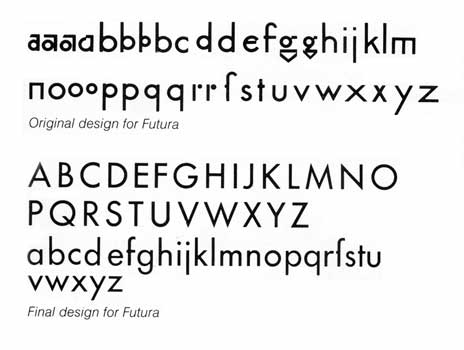
[Suche Bild] Original Designs der Futura von Paul Renner
ich bräuchte für eine Studienarbeit ein Bild von Renners Original Entwürfen der Futura (siehe oben) in guter (na ja, sagen wir mal in besserer) Auflösung. Google bringt mir keine brauchbaren Bilder. Weiß jemand wo ich da fündig werden könnte?
in Christopher Burkes «Paul Renner - The art of typography» finden sich eine große Doppelseite und halbseitige Abbildungen von Renners Reinzeichnungen.
Solche Scans dürften auf die Schnelle die beste Methode sein, ordentliches Bildmaterial aufzutreiben!
Aber vielleicht gibt es ja schon Scans im Netz?
Die Futura von E+F oder URW++ (ich glaube, es war E+F) enthält aber bestimmt nur die bekannten Sonderzeichen agmn&, die es auch in der Bleisatz-Type gab.
Burke stellt aber auch zB. 11 unterschiedliche g Varianten vor (Seite 92), die aus der Entwurfszeit (1925) der Futura stammen.
In dem Buch werden wirklich jede Menge Varianten vorgestellt. Es lohnt sich!